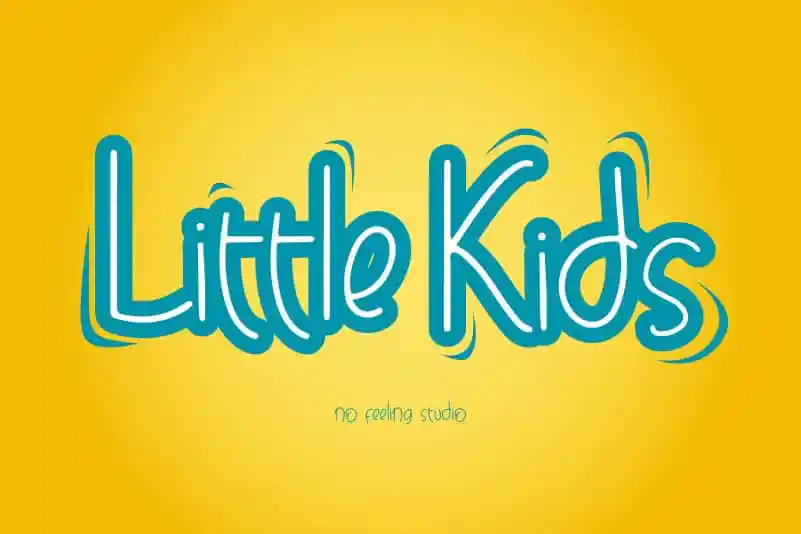
Little Kids Display Font – Fonte Grátis
Little Kids Display Font
A Little Kids Display Font é uma fonte tipo com tema de criança que traz a energia e a inocência dos pequenos para seus projetos. Esta fonte possui um tom descontraído, brincalhão e cheio de encanto, ideal para adicionar um toque jovial e engraçado a qualquer design. Seja você criando uma identidade visual para uma loja infantil, ou adicionando um charme deslumbrante à sua próxima apresentação de PowerPoint, Little Kids Display Font trará vida aos seus projetos de forma única e divertida. Inspirada no universo vibrante e imaginativo dos pequenos, esta fonte não apenas dá um toque jovial a seu trabalho, mas também o enche de um coração encantado que reflete a pureza da infância. Seria uma ótima adição para qualquer designer buscando dar um ar mais jovial e descontraído às suas criações.